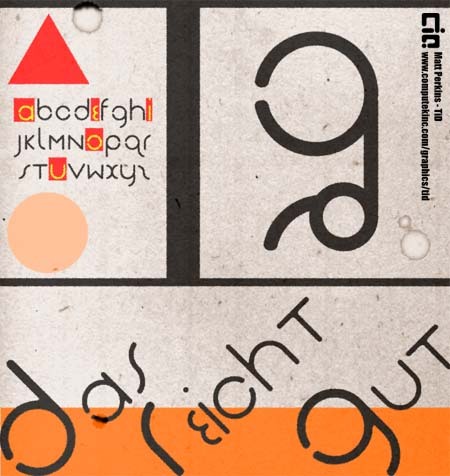
Das Reicht Gut von Matt Perkins ist eine kostenlose, futuristische Display-Schrift, die Sci-Fi-Elemente mit eleganten, geschwungenen Linien weicher wirken lässt. Die abgerundeten, gleichmäßigen Striche und die offenen, luftigen Formen wirken zugleich retro und zukunftsorientiert – wie Neonröhren, die zu klaren, modularen Buchstaben gebogen wurden. Der Rhythmus ist ruhig und ausgeglichen, sodass die Schrift selbst in großen Größen gut lesbar bleibt und dabei ihren markanten, stilisierten Charakter behält.
Mit Das Reicht Gut verleihen Sie Tech-Branding, Sci-Fi-Postern, minimalistischen Verpackungen, Album-Covern, App-Headern und Event-Flyern eine moderne, geschmeidige Note – ganz ohne harte Geometrie. Diese kostenlose Schrift glänzt besonders, wenn sie in mittleren bis großen Größen atmen kann. Kombinieren Sie sie für den Fließtext mit einer schlichten Grotesk oder einer geometrischen Sans, um alles klar und lesbar zu halten.